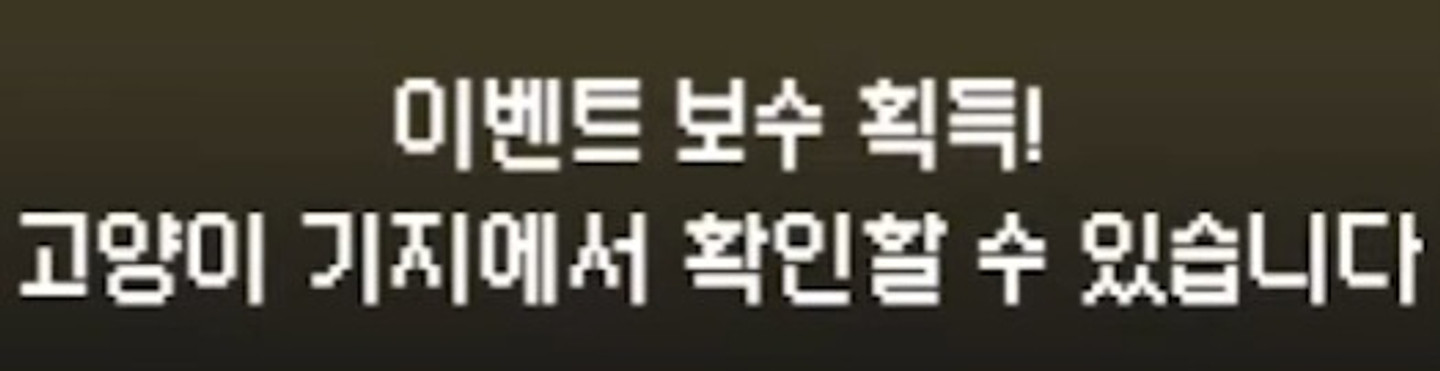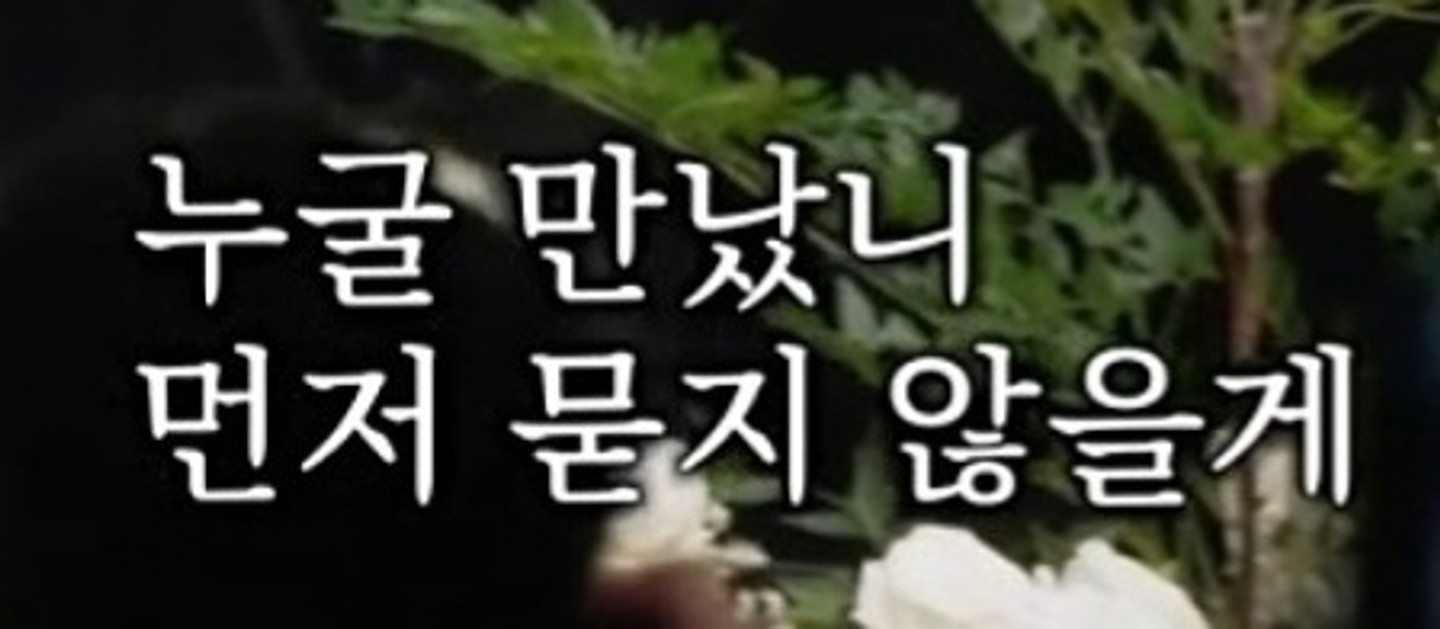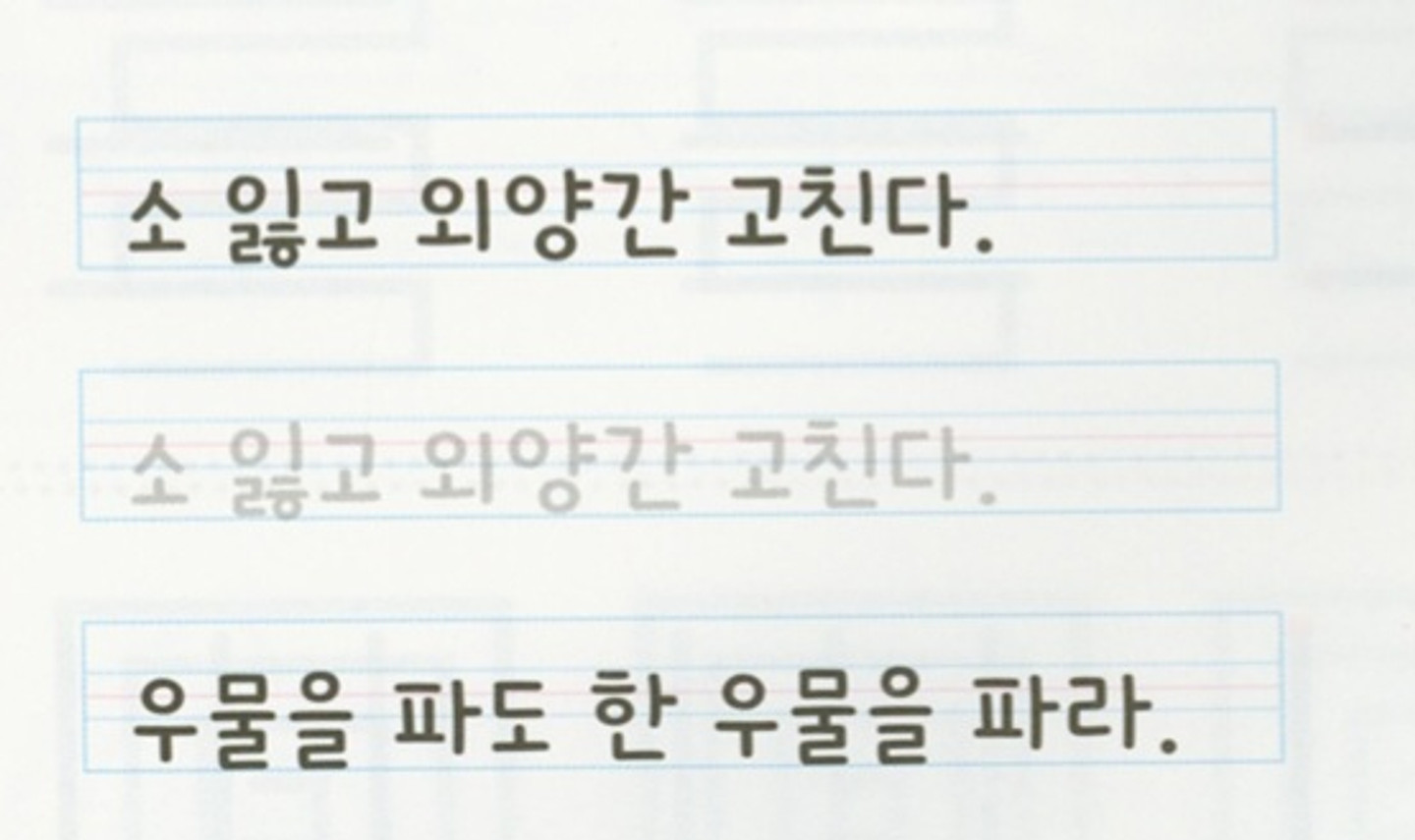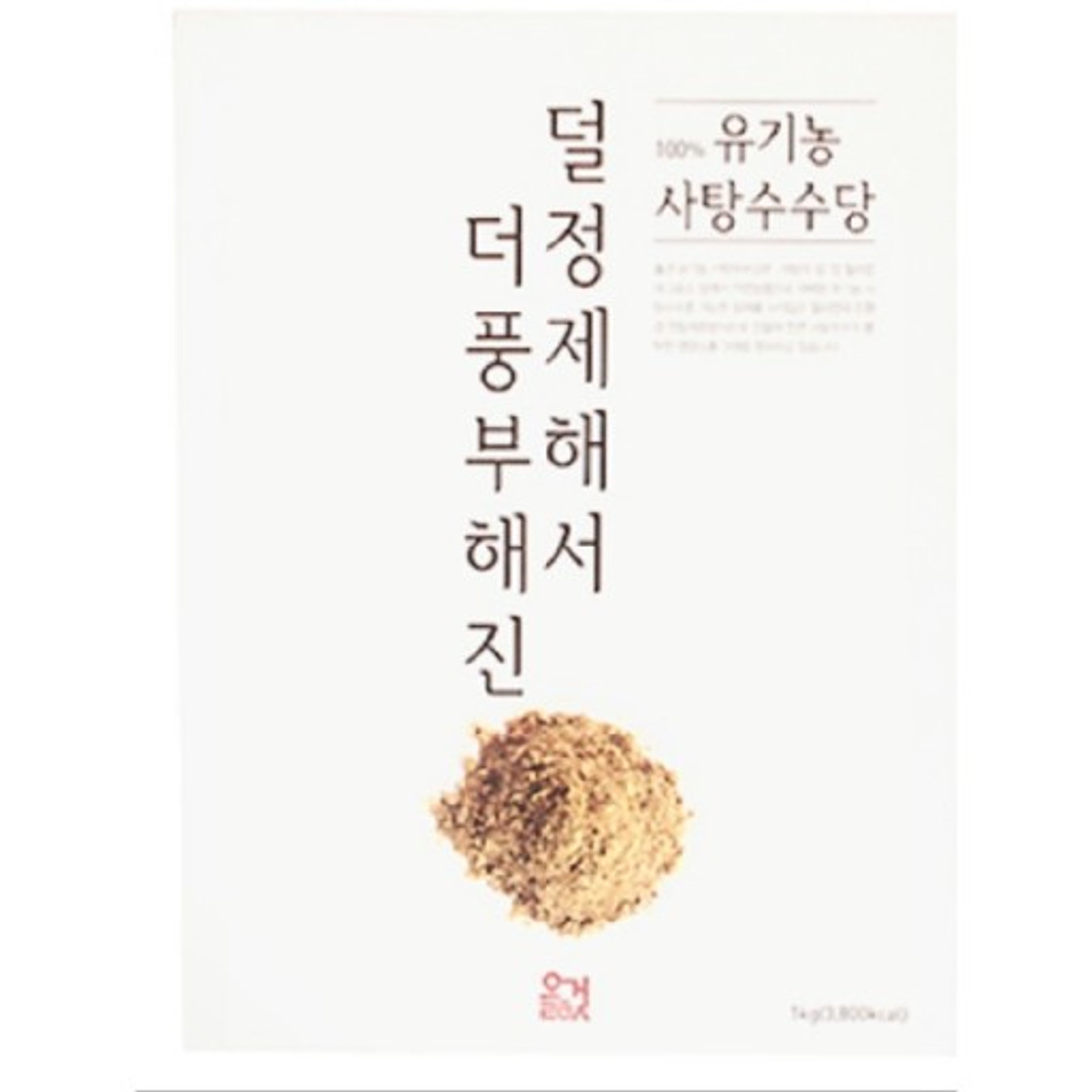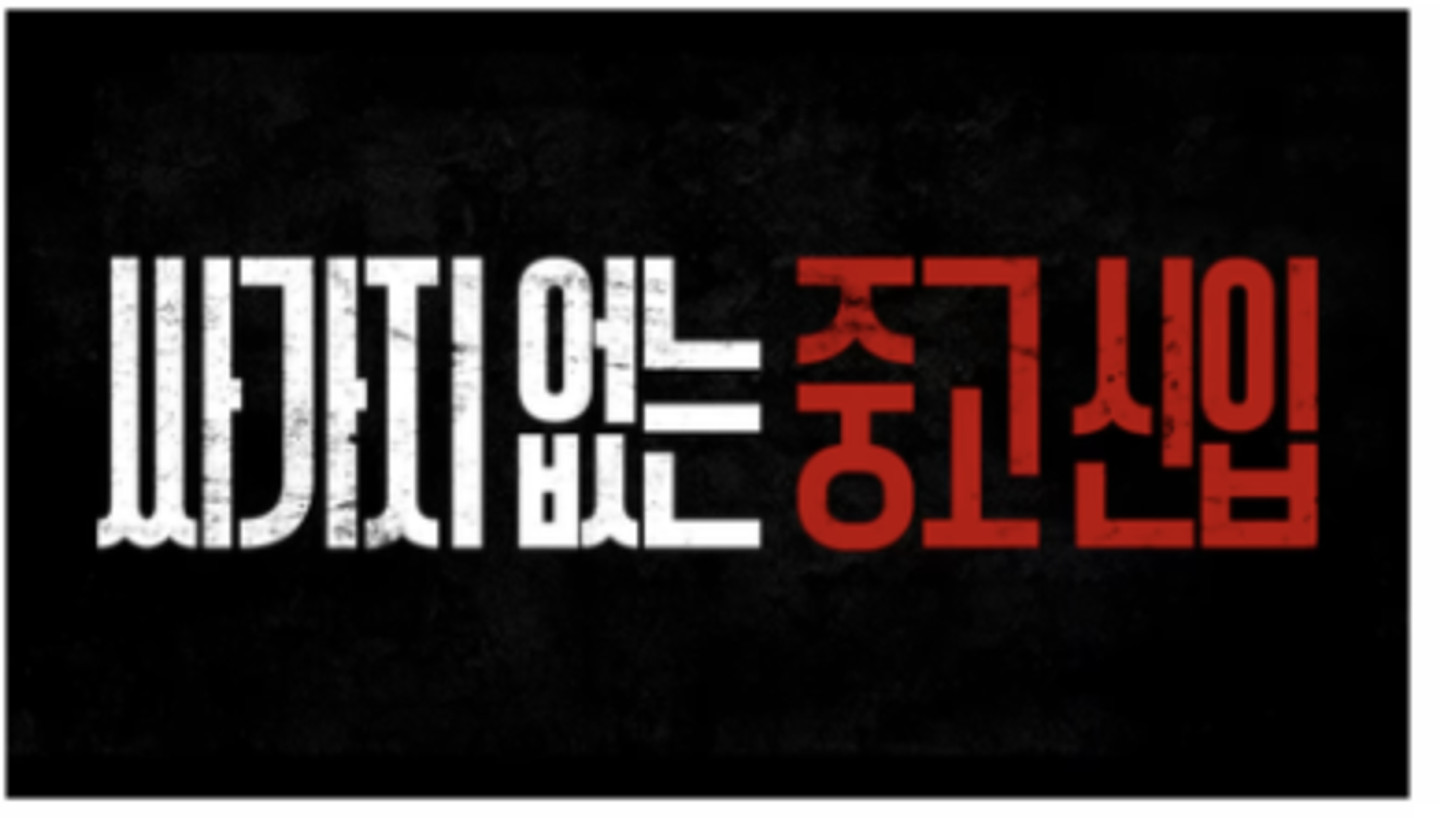
W가 사진처럼 되어있는 영어폰트 궁금해요
캡컷에 있는 십대라는 폰트인데 찾아봐도 없어서 ㅜㅜ 아시는 분?
폰트를 찾을 수 없네요 도와주세요
이 폰트 어떤 폰트인지 알 수 있을까요?
이런 폰트가 있을까요?
이 서체가 어떤건지 아시는 분..!
해당 글씨체 폰트가 무엇인지 궁금합니다. 추가로 무료인지 유료인지도 궁금해요 알려주시면 감사하겠습니다 :)
변형된 폰트같긴한데 혹시 정보 아시는분 있으신가요
안녕하세요 폰트 문의 드립니다 분명 무료같은데 (기억오류일수도있음) 못찾겠어서요
책 제목의 폰트가 뭘까요?
혹시 이 폰트 뭔지 아시는 분 계실까요?
해당 폰트 혹시 어떤 걸까요? 검색해도 나오지 않아 질문드려요
밥 먹고 갈래요? 라는 웹툰에 나오는 글씨첸데 이거를 쓰고싶어서요,, 비슷한 폰트라도 찾아주세요ㅠㅠ
이 폰트가 뭘까요..?!
이거 무슨 폰트인지 아시는 분 알려주세요 ㅠㅠ
폰트가 각져있어서 시인성이 좋아보이는데 무슨폰트일까요...
무슨 폰트 일가요ㅠㅠㅠ 제바류ㅠㅠㅠ
사진과같음
위아래 폰트 아실까요?
푸라닭 젠틀 고딕과 비슷한데 달라요. 무슨 폰트일까요?
이거무슨폰트인가요~
이 폰트 뭘까요!? 비슷하게 만든 레트로 폰트말고 진짜 저 폰트요!
보복운전 폰트 뭔가용
이 폰트좀 알려주세요!
블레이드 앤 소울 인게임 등장인물 소개할때 나오는 서체인데 아시는 분 계시나요
이 글씨체랑 비슷한 폰트 찾아주실수 있으실까요?
여기 1999 무슨 폰트인가요???
이진이 유튜브에서 사용된 폰트입니다! 혹시 아시는 분 계신가요?
이런 손글씨랑 비슷한 폰트 있을까요?
보라색 계열 폰트도 부탁할게요
무슨 폰트일까요ㅜㅜ
교재에 큰 글씨로 써 있는 거는 무슨 폰트가 사용된 건가요??
학교 과제를 하고 있는데 이 폰트가 어떤건지 기억이 안나요 ㅠㅠ 눈누에서 다운 받은게 확실해요 ㅠㅠ
이 폰트 알고싶어용~!!!!
무슨 서체일까요? 비슷한 건 아는 데 딱 이 서체는 모르겠네요
무슨폰트인가요?!
안녕하세요 혹시 이름에 써져있는 폰트가 뭔지 알 수 있을까요??ㅠㅠ
친구가 이 폰트를 애타게 찾고있어요 카톡 기본 폰트 목록에 있었는데 갑자기 업데이트 하면서 사라졌대요 이름 아시는 분 있나요?? ㅠㅠ
영상 속 글씨가 꿀렁꿀렁하는 애니메이션이 적용된 상태에서 캡쳐한거긴 한데 혹시 어떤 폰트인지 알 수 있을까요
이폰트 궁금해요 ㅜㅜ아무리 찾아도없어용 근데릴스에서 이폰트는 진짜마니 봤어요 아시는분?
무슨 폰트일까나요...?
무슨 고딕 폰트인지 알 수 있을까요 . ?
이 폰트 멀까영
이 글씨체를 알려주세요
무슨 글씨인지 궁금해요!!!!
이 영문폰트 아시는 분 좀 부탁드려요~`
정확한 폰트 이름이 궁금합니다.
이 폰트가 넘무 궁금함니다
이 폰트 무슨 폰트인가요?
이 폰트 너무 궁금합니다 ㅠㅠㅠㅠ
이 폰트먼가영
폰트 너무 이쁜데 뭘까요 🥹
영상에 나오는 자막 폰트가 너무 예쁘고 깔끔해서 혹시 어떤 폰트를 사용하시는지 알 수 있을까요? 여러 폰트를 비교해보니 조선굴림체와 가장 비슷한 것 같긴 한데, 기울이거나 두껍게 해봐도 미묘하게 다른 부분이 있어서 정확한 폰트 이름이 궁금합니다! 혹시 알려주실 수 있으시다면 너무 감사하겠습니다! 🙏🏻
갤럭시에 나눔바른펜과 비슷한 폰트 있을까요? 아니면 나눔 바른펜과 비슷한 폰트 추천해주세요 ㅠㅠㅠㅠ 제발 ㅠㅠㅠ s25+로 바꿨더니 폰트 죄다 개밤티라 힘 빠져요.. 나눔바른펜 아니면 안되는데